사적으로 아름다운-1 : <시청각 문서 1-[80]>
연재 ‘사적으로 아름다운’을 통해 세상에 존재하는 여러 책 중에 조금 더 필자 개인에게 아름답게 다가오는 책에 대해 자세하게 이야기한다.
사적으로 아름다운 – 1 : <시청각 문서 1-[80]>
현시원 외 지음, 시청각, 2015
<시청각 문서 1-[80]>는 종로의 전시장 시청각에서 그간 ‘시청각 문서’라는 이름으로 각각 발행했던 문서를 모은 책이다. 이 책에서 우선 주요한 것은 페이지 넘버다. 총 17가지 글을 엮은 80쪽의 책에서 ‘쪽’이 그토록 두드러지는 까닭은 무엇일까. 이 글을 끝까지 이어가려면 이 책을 조금 더 자세히 봐야 한다.
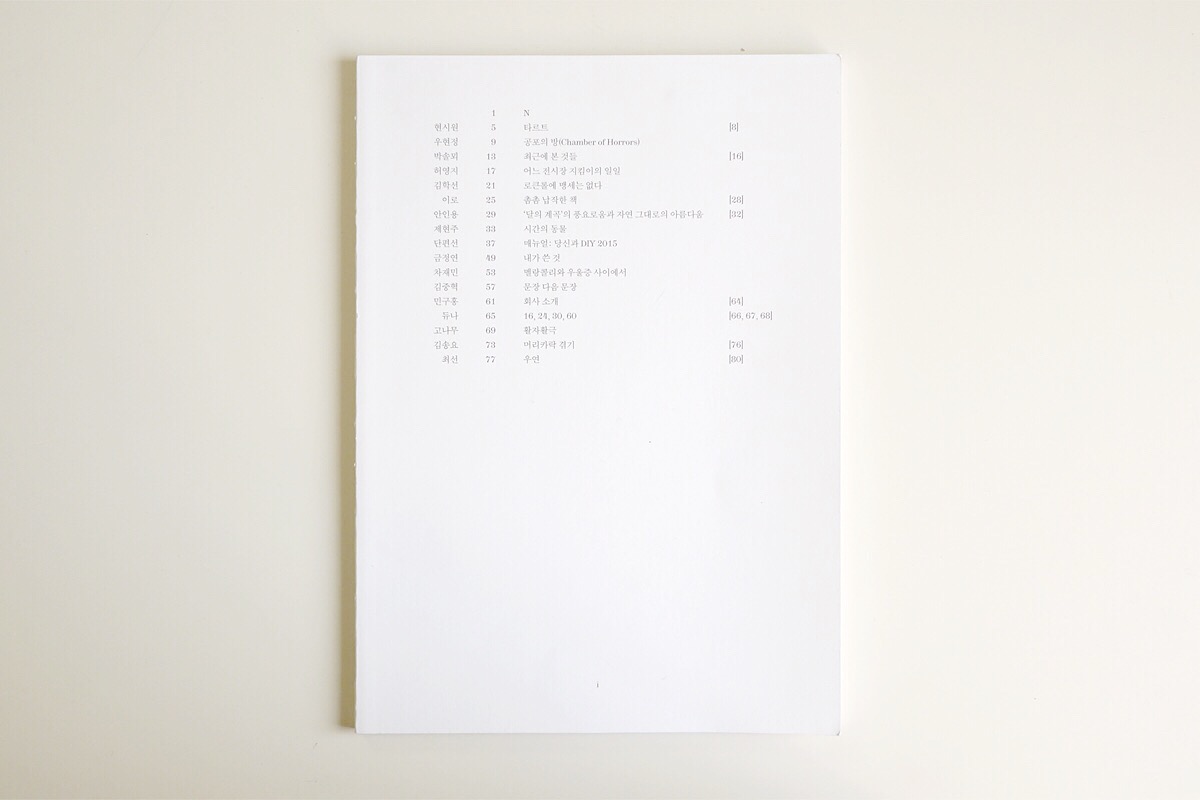
먼저 표지를 본다. 작가와 해당 페이지, 제목이 먼저 보인다. 이 책의 제목은 두 번째 페이지에서 처음으로 등장하는데, 그것은 ‘무엇이 더 앞설 것인가’의 판단에 따른 것처럼 보인다. 각 낱장의 문서가 먼저였고, 서적이 다음이다. 그때 전체 제목보다 더 중요한 것은 책의 구성이다. 문패보다 뼈대를 먼저 보아야 하는 건축물이다. 그 뼈대에서 바로 이해가 가지 않는 것은 우측 대괄호에 포함된 숫자들, 그리고 하단의 영문 소문자다.
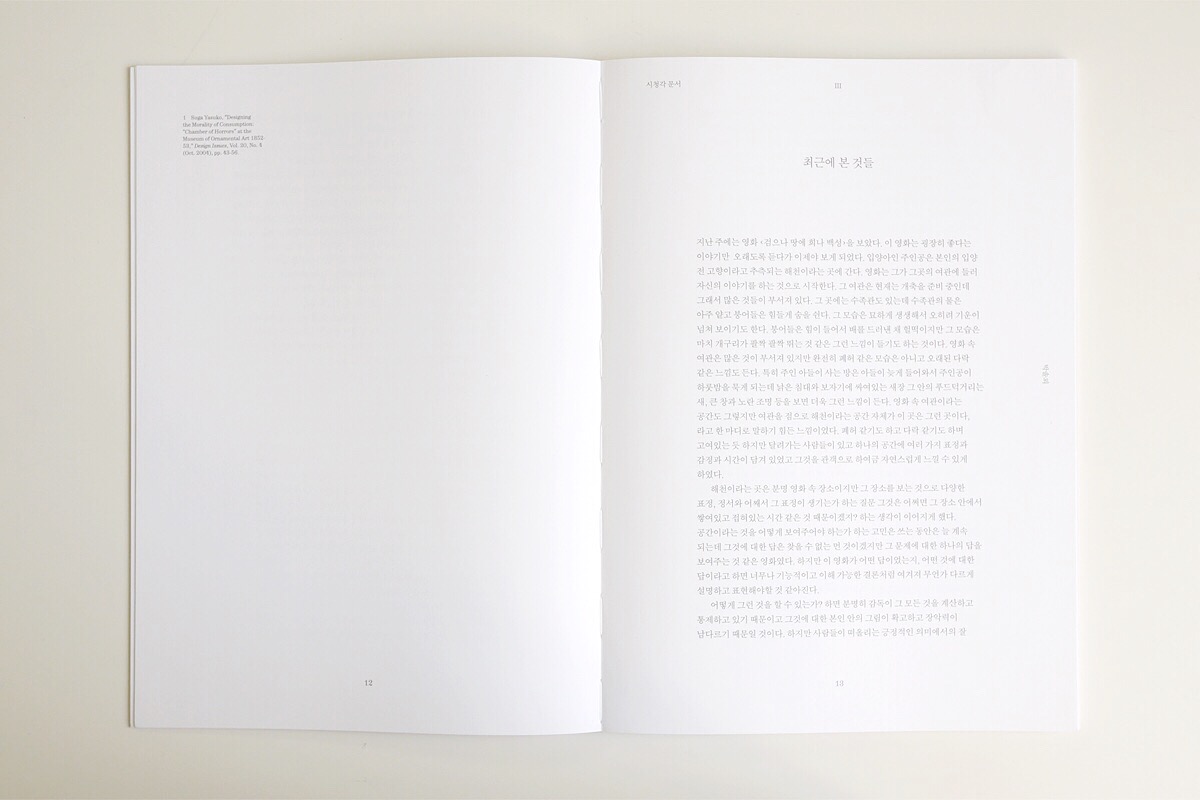
책을 넘겨 보면 작은 미스터리가 곧 풀리는데, 대괄호는 책 전체에서 하나의 규칙에 따라 사용된다. 텍스트가 전혀 없는, 공백의 페이지에 대괄호와 그 쪽수가 표기된다. 그리고 로마자는 본문 80쪽을 제외한 앞뒤 8쪽의 순서를 표기하는 데 쓰였다. 처음 이 두 가지 요소를 인식하고 나서, 대단히 재밌는 기술이라고 생각했다. 왜냐하면, 이 책 전체를 통틀어 그 어떤 ‘면’도 쓰이지 않기 때문이다. 백색의 종이와 1도의 먹색 글자들이 이 책의 전부다. (가느다란 선은 두 번 쓰였다.) 그러니까 <시청각 문서 1-[80]>에서 책의 바깥(표지와 뒤표지)을 안(본문)과 구분케하는 요소는 전통적인 ‘제목과 이미지, 색상’, 다시 말하면 ‘표지로 규정된 표지’가 아니라 작고 특수한 약속(로마자 숫자)이다. 이 책을 디자인한 홍은주, 김형재 디자이너는 책에 수록된 원고를 독립된 문서일 수 있도록 설정한다. 책등을 감싸지 않은 사철제본 역시 문서를 그저 ‘엮기만’ 하려는 디자인 전체 방향에 가장 잘 어울린다.
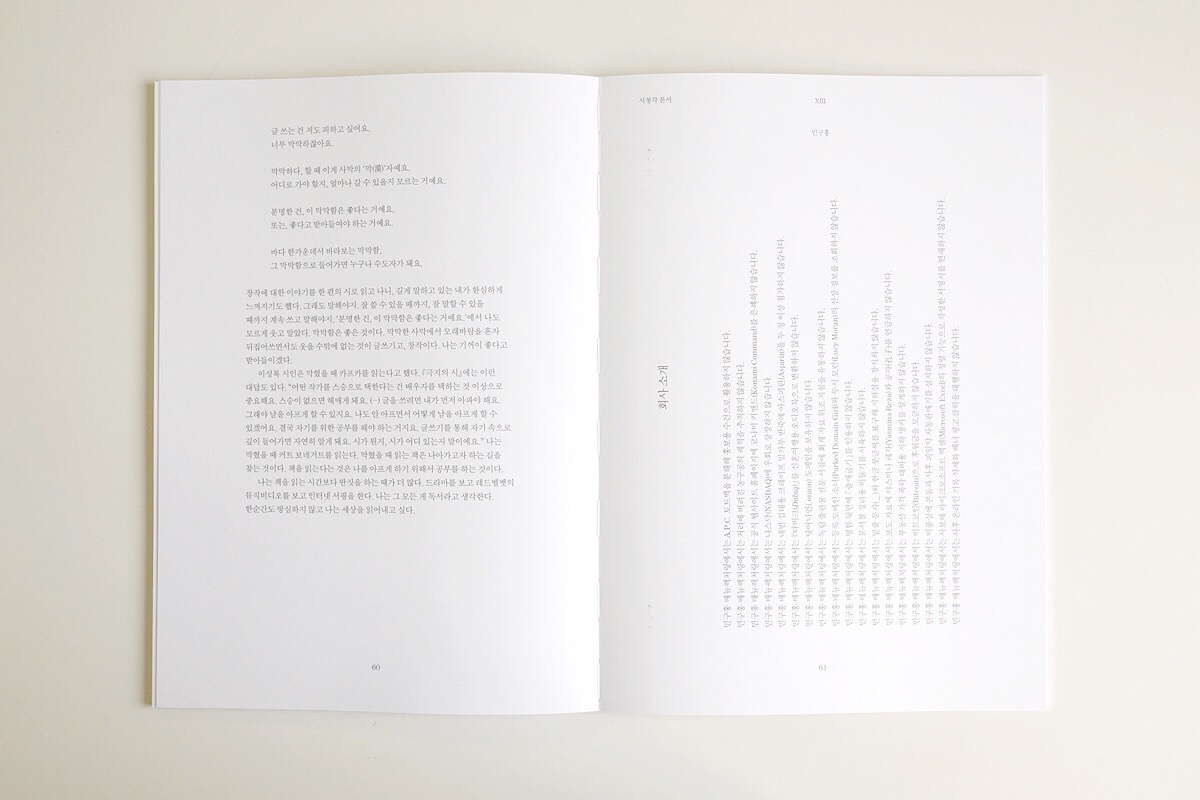
책을 전부 읽은 뒤 다시 제목으로 돌아오면 ‘1-[80]’ 부분이 특수하게 다가온다. 문자가 표기된 페이지에서 시작하여 공백의 페이지로 끝난 것이다. 그것은 “기록한다는 것은 하찮은 일이다”라는 문장으로 시작하는 책 서문이나 “시청각 문서는 문서로서는 이미 실패한 시도”라는 전시 서문과도 맞물린다. 그런데 그 공백은 허망하게 비어있지 않다. 공백 역시 자신만의 규칙을 세워 공백으로서의 역할을 한다. 그동안 우리는 현란한 색과 그래픽, 이미지를 채워서 끝내 서로의 멋을 잡아먹고 있는 책들을 본 기억이 있다. 이 책의 디자인은 문서를 문서로 배려하면서 동시에 책일 수 있게 하는 유일한 방법처럼 보인다. (과장을 조금 섞어서) 각 페이지가 글자가 새겨진 무척 얇은 돌판을 포개어 놓은 것처럼 느껴진다. 낱장에 질서와 무게를 부여할 수 있는 힘이다. 아름다운 디자인이자 아름다운 책이다.